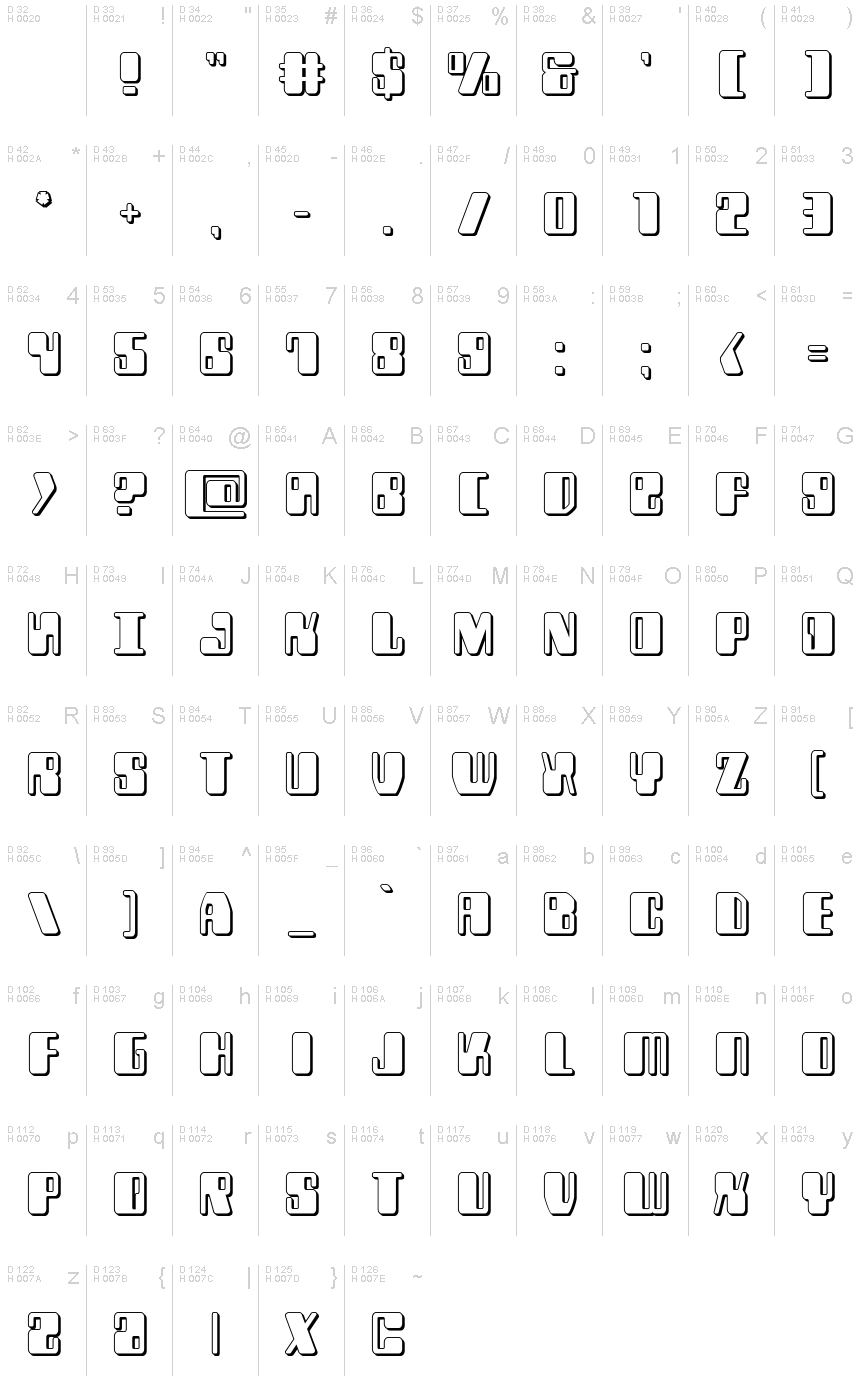
Zyborgs 3D von Iconian Fonts ist eine kostenlose, futuristische 3D-Display-Schrift mit einem massiven Arcade-Sci-Fi-Charakter. Die Buchstaben wirken zugleich aufgeblasen und gepanzert, mit abgerundeten Ecken, tiefen Einschnitten und einem konturierten 3D-Effekt, der der Schrift das Aussehen eines Roboter-Spielzeugs oder eines Spiel-Titelbildschirms verleiht.
Sie eignet sich hervorragend für Gaming-Logos, plakative Überschriften, Comic-Cover, Streamer-Grafiken und Titelkarten, bei denen kurze Wörter einen kräftigen, mechanischen Ausdruck benötigen. Da es eine kostenlose Schrift ist, passt sie auch gut zu Fanzines, Veranstaltungsflyern und Monogrammen, besonders wenn die Buchstaben eher wie weich abgerundete Blöcke als wie harte, industrielle Geometrie wirken sollen.
Zyborgs 3D